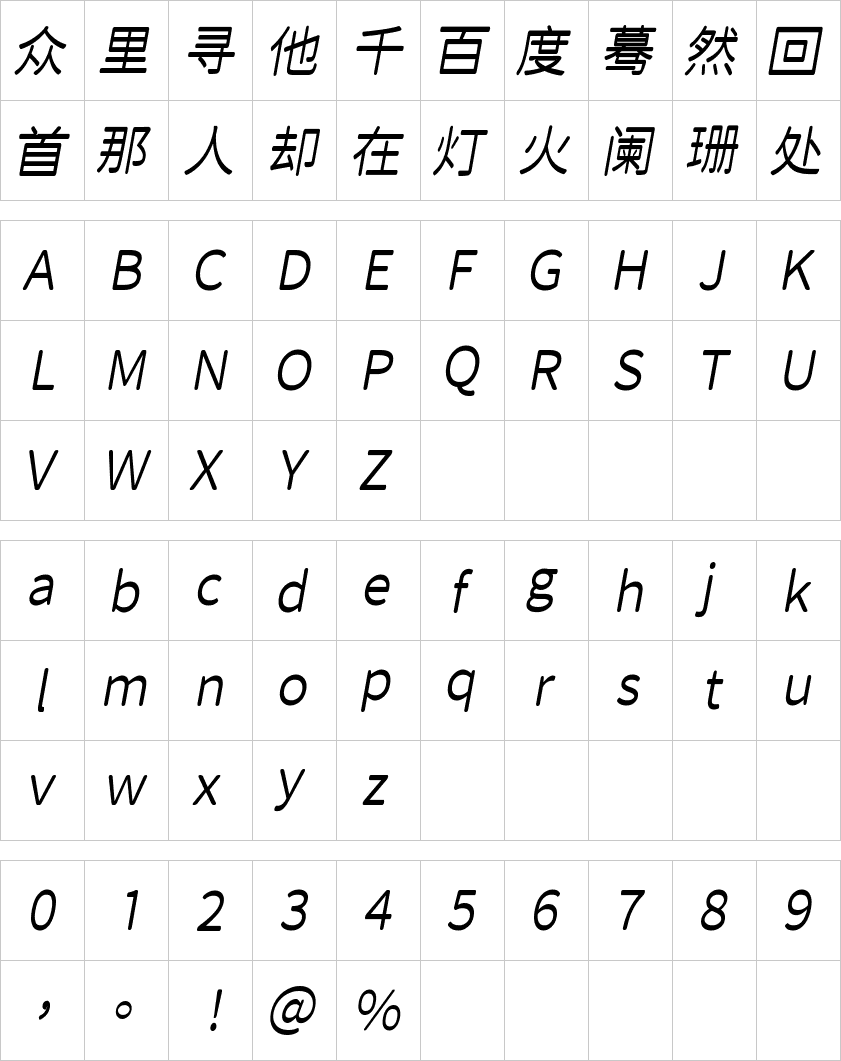
江城月湖体
江城月湖体是大神刘鹏发布的江城系列字体又一款力作,江城月湖体基于江城圆体改造而成,和江城知音体相反,是把江城圆体横向增粗处理,纵向减细处理,并把字体进行倾斜10度,而且该字体拥有3个字重。
这款字体字形灵秀清美,横粗竖细的风格颇为特别,圆润的笔画中又带着一点动感,比较适合用作正文,标题,偏柔美风格的设计。刘鹏大神已经在猫啃网上发布了江城知音体、江城斜黑体、江城斜宋体、江城正义体、江城圆体等多款免费商用字体供广大设计师使用,猫啃君在这里再次对刘鹏大神表示感谢!